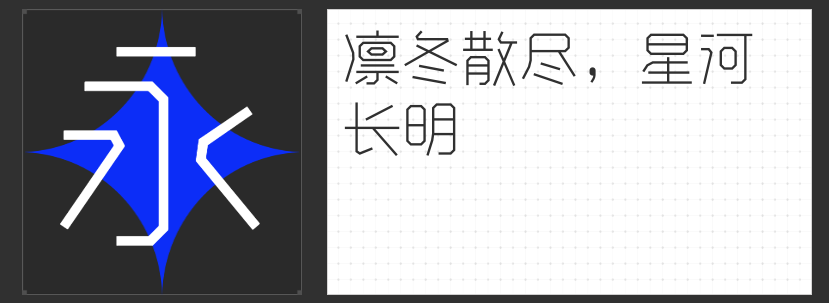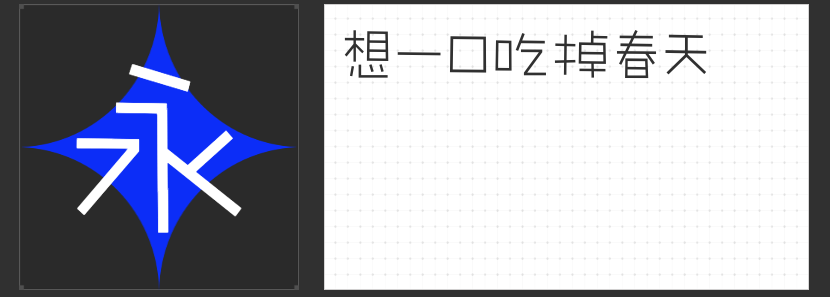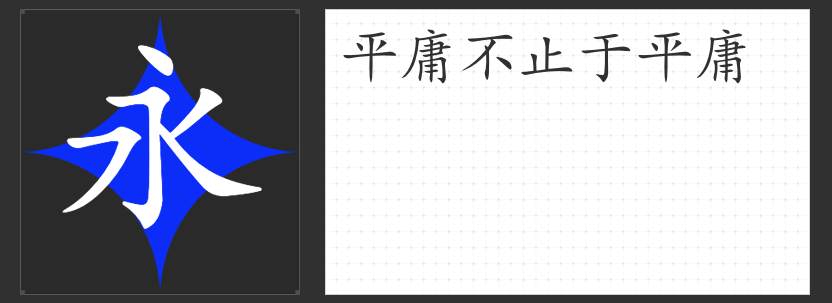
塑造品牌视觉灵魂:四款字体解锁多元设计语言
在品牌设计中,字体不仅是信息传递的载体,更是传递品牌调性的视觉符号。以下四款字体以其独特的设计语言,为不同领域品牌提供精准的视觉解决方案,助力构建深入人心的品牌记忆点。
一、高手庆科智雅体 细体
这款直线型字体以中宫略大的布局构建视觉张力,横竖笔画等粗处理强化理性气质,连笔折笔的细节设计打破呆板,切口优化后的尖锐线条增强现代感。西文字符延续中文的直线基因,通过切角处理达成风格统一,尤其适合科技、金融或高端制造业品牌——既传递专业严谨性,又不失设计巧思。
二、 励字敲可爱简 细体
将手写体的温度注入品牌基因,这款字体以圆润线条弱化棱角,适度省略笔画营造轻松感。其独特的“未完成感”设计,仿佛孩童用心书写的痕迹,为文创、儿童产品、甜品品牌注入温暖治愈力。在年轻化市场中,这种带有瑕疵美的设计更易引发情感共鸣。
三、造字侠热辣隶简
将隶书扁宽结构与现代极简美学融合,这款字体通过横笔开张对称、竖钩直线概括,在保留历史厚度的同时注入现代锐气。撇捺的粗细过渡自然流畅,既适合作为国潮品牌的主标题字体,也能为文化展览、传统老字号焕发新生——在复古与现代间架起视觉桥梁。
四、 励字楷体简繁
以楷体为蓝本重塑的这款字体,将尖锋顿笔转化为数字时代的精致表达。圆润挺拔的笔画兼具传统书卷气与现代设计感,简繁双版本设计更适配两岸三地市场。适用于高端文化品牌、艺术机构或奢侈品领域,以字体传递“时光淬炼”的品牌价值。
从理性秩序到文化叙事,四款字体构建起品牌设计的多维表达体系。在全球化市场中,选择一款与品牌基因共振的字体,不仅是视觉投资,更是对目标受众的精准对话——让文字成为品牌灵魂的显性表达。